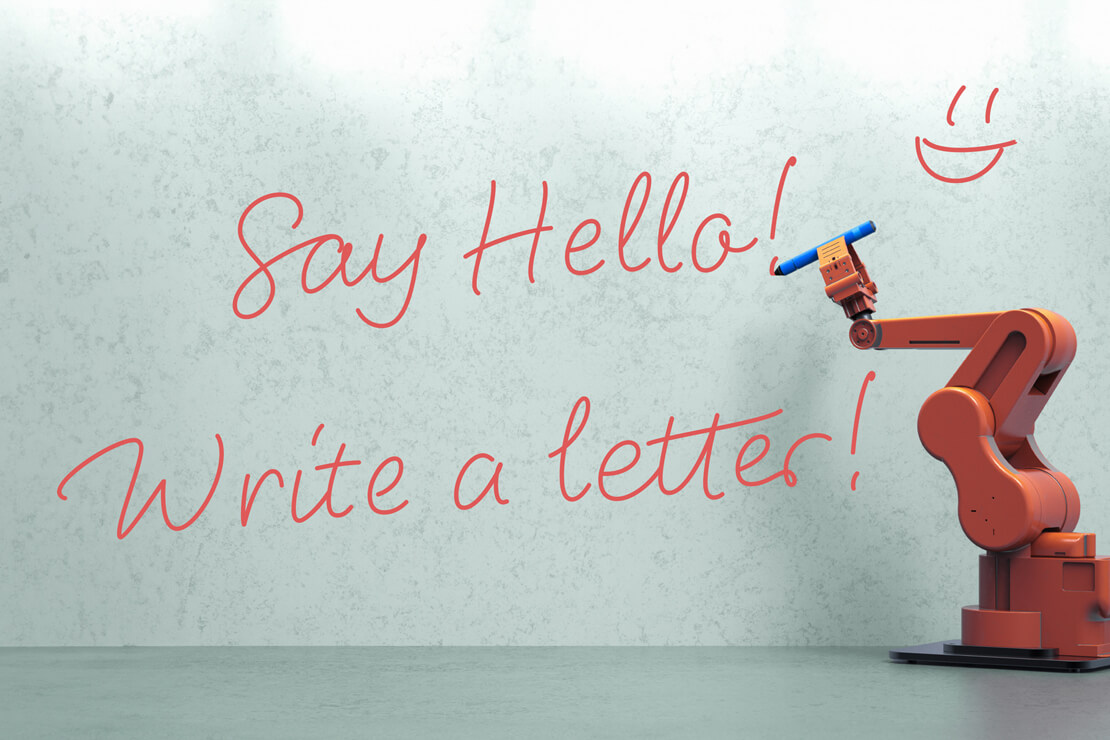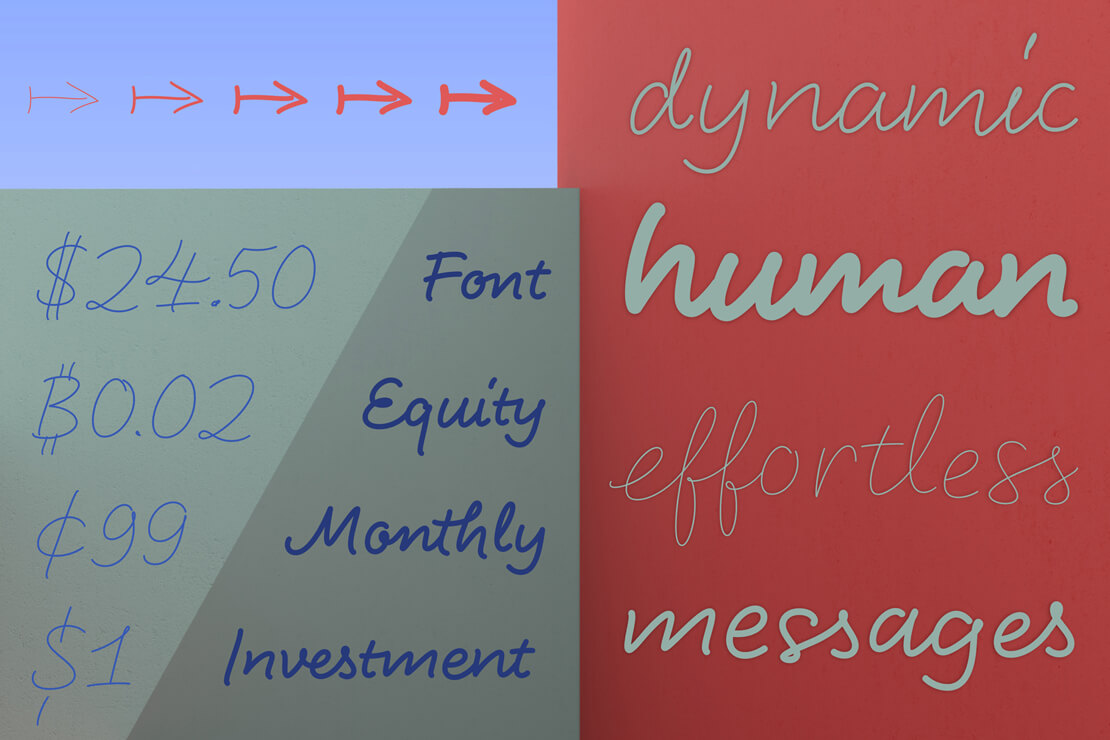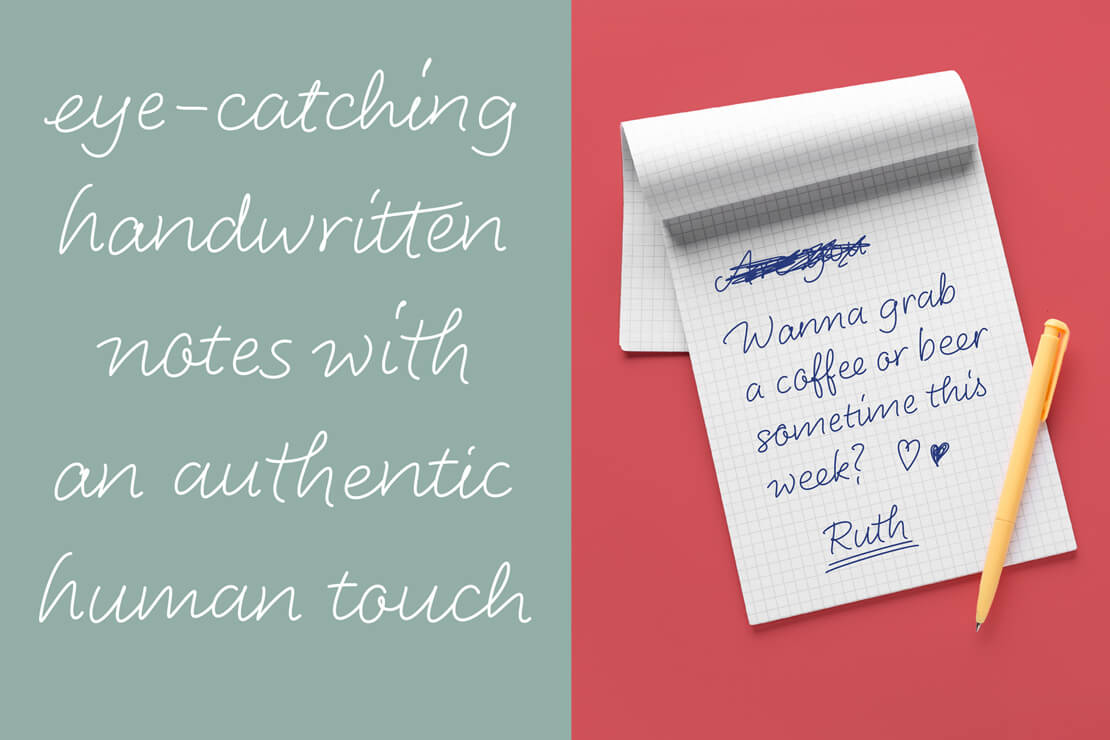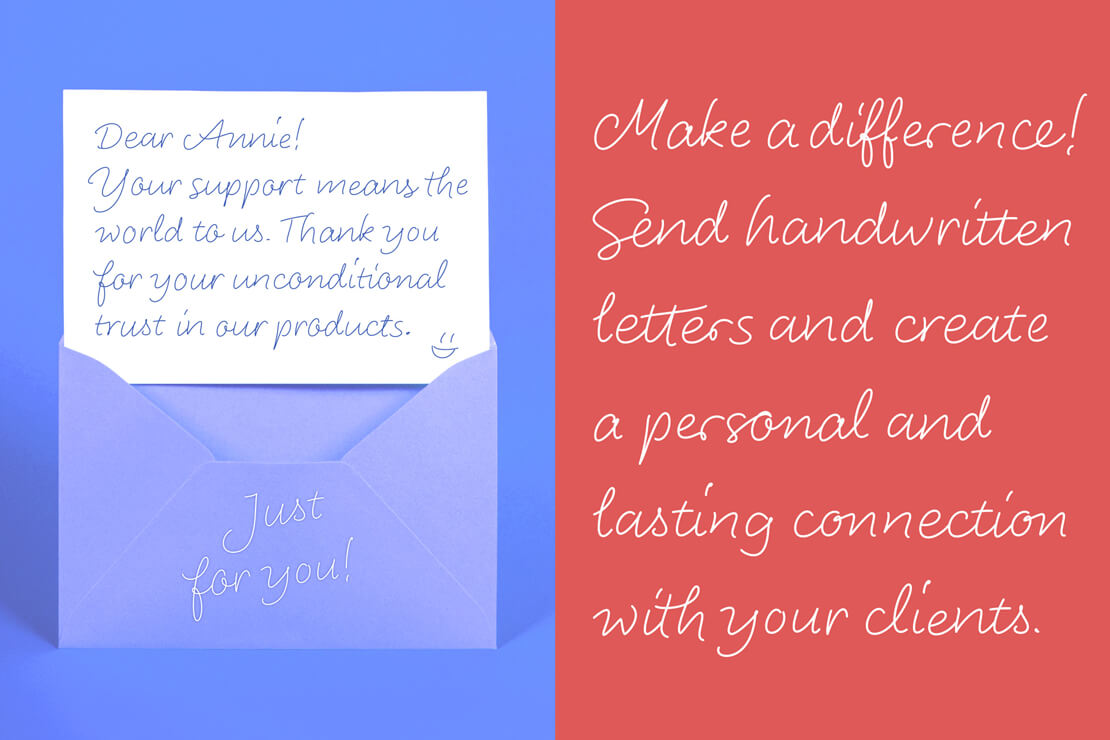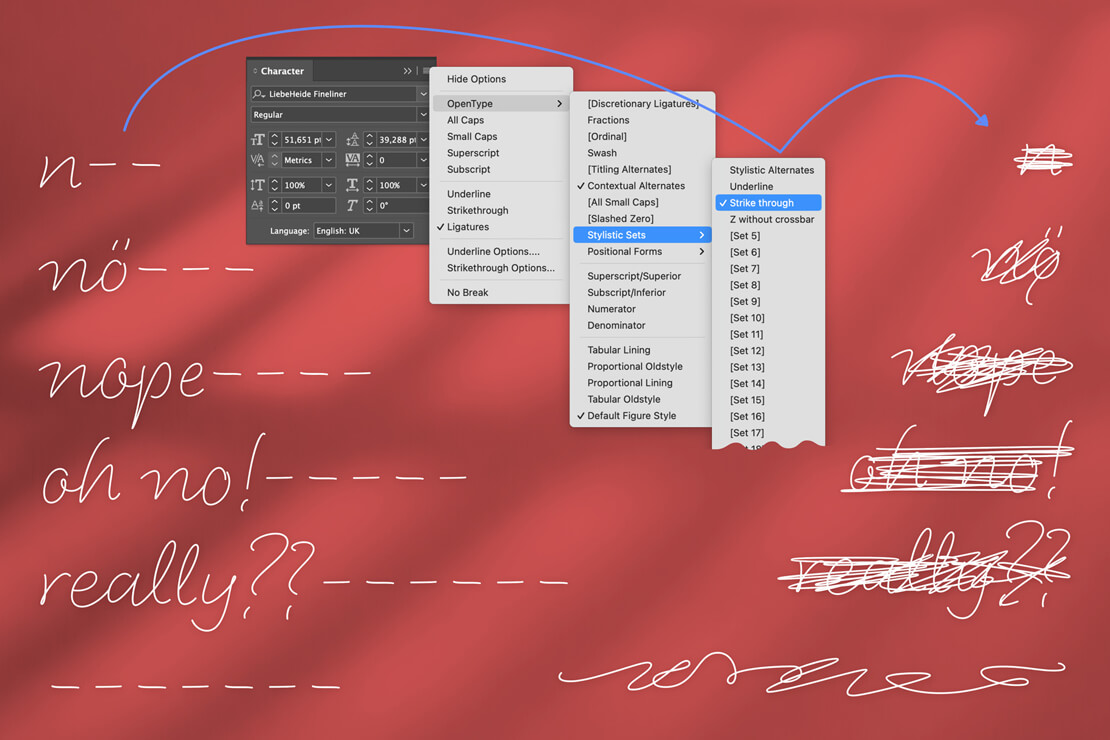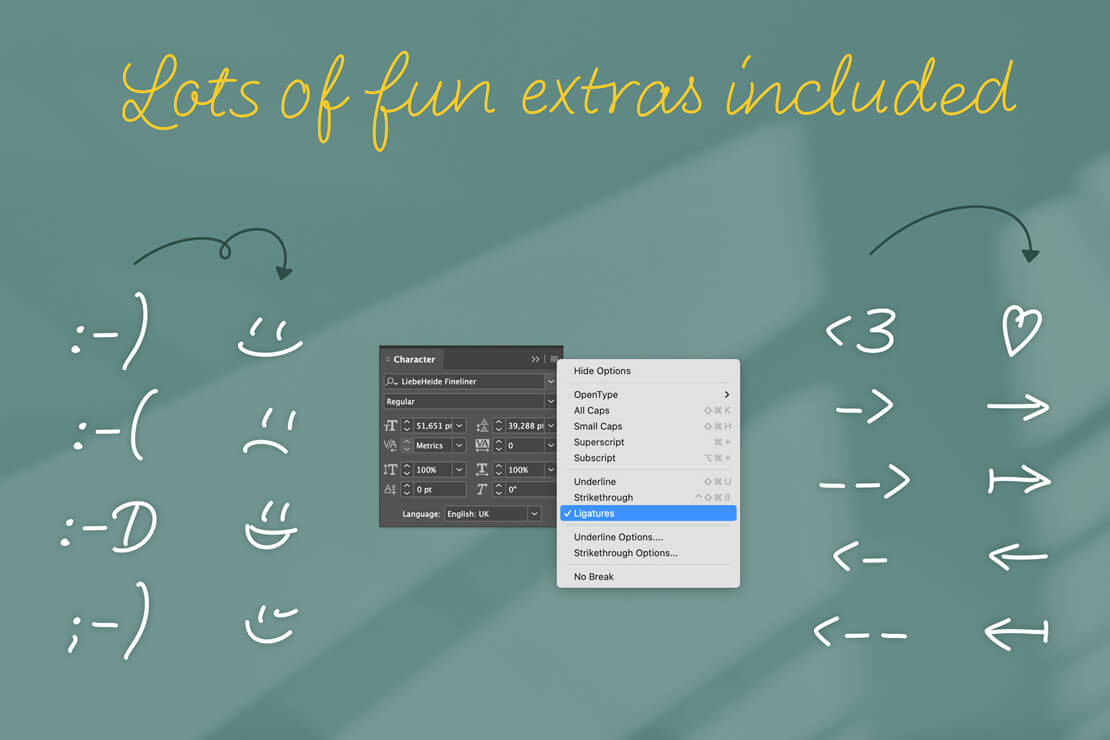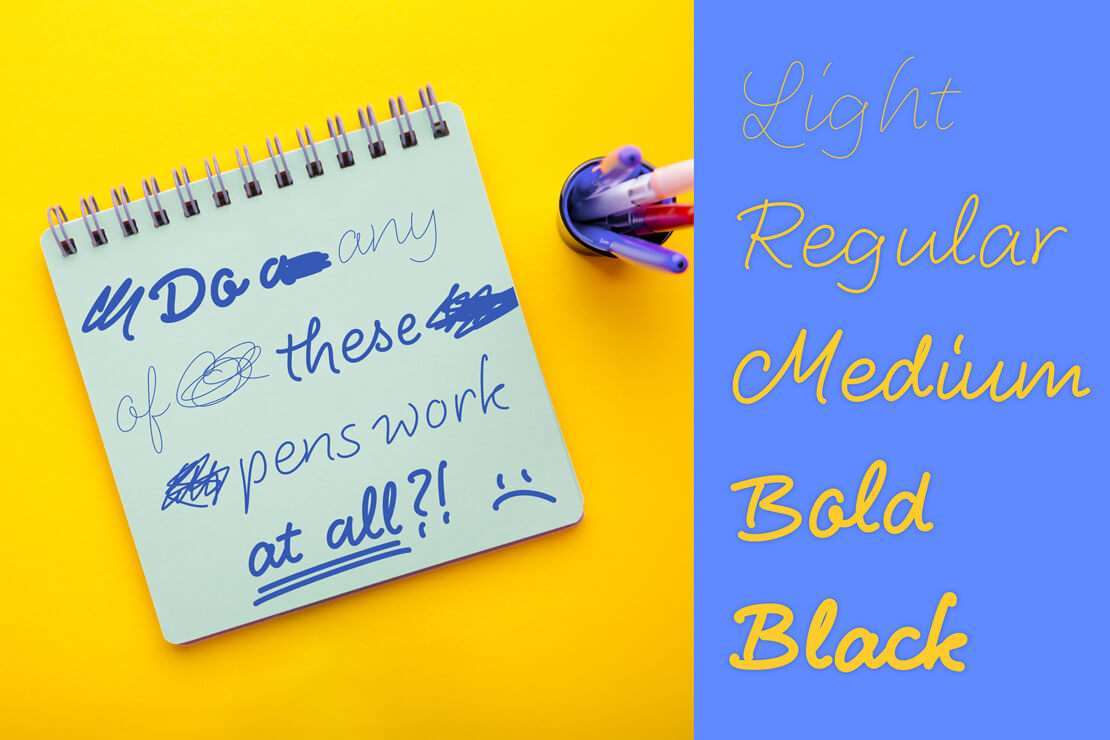
LiebeHeide: Die Fineliner-Schrift
Ulrike Rausch präsentiert mit »LiebeHeide Fineliner« eine neue Schrift, die den Eindruck erweckt, von Hand mit einem Fineliner gezeichnet worden zu sein. Durch zahlreiche Ligaturen und Varianten entstehen dabei natürlich wirkende Buchstabenverbindungen, die den Text lebendig und fließend erscheinen lassen.
Bereits zuvor hatte Rausch mit LiebeHeide einen preisgekrönten Color-Font entwickelt, der das Schriftbild eines Kugelschreibers authentisch nachahmen kann.
Da nicht alle Programme dieses spezielle Fontformat unterstützen, gibt es nun mit LiebeHeide Fineliner eine Vektor-Version. Diese greift die stilistische Anmutung von »LiebeHeide« auf, ist aber optisch an einen Fineliner angelehnt.
LiebeHeide Fineliner bietet dieselben klaren Linien und eleganten Kurven wie die Kugelschreiber-Version und verleiht Texten dadurch eine persönliche, freundliche Ausstrahlung.
Durch die zahlreichen Buchstabenvarianten und alternativen Verbindungsstriche passt sich die Schrift dem jeweiligen Kontext an und erhält dadurch ihren persönlich wirkenden Charakter.